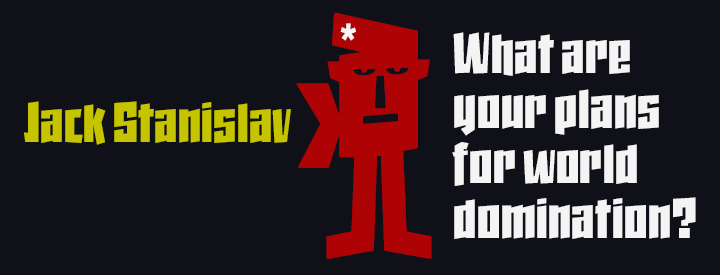
Tipografía muy condensada de trazo grueso y aspecto divertido [...]
Tipografía muy condensada de trazo grueso y aspecto divertido para titulares y publicidad donde se busca ahorro de espacio a la vez de originalidad. La inclinación super…